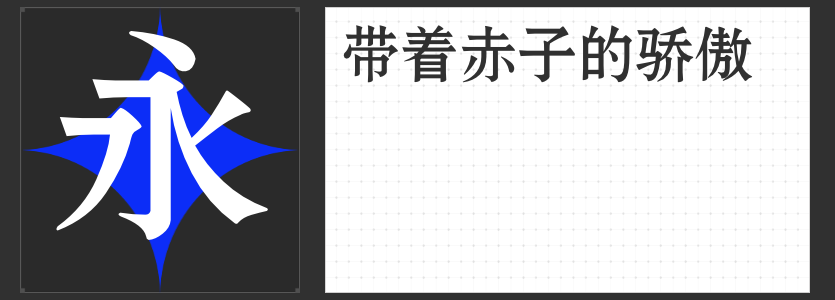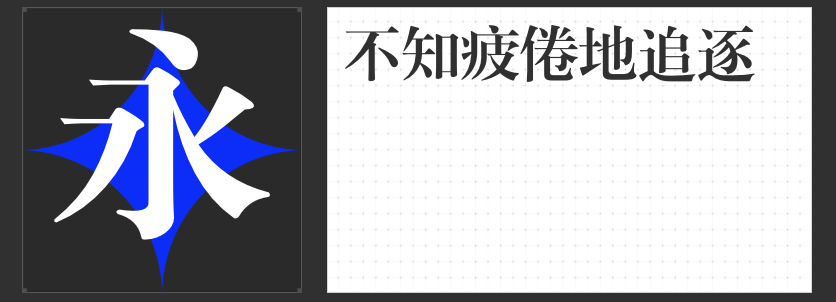
宋体之美:四款精选字库字体推荐
在字体的海洋中,宋体以其独特的韵味和端庄的风格,赢得了众多设计师的青睐。今天,我们为大家推荐四款精心挑选的宋体字体,让我们一同领略宋体的独特魅力。
1.励字大标宋简繁
以其横轻竖重、末端装饰精美的特点,展现了老宋体与黑体的完美结合。笔画间粗细变化自然,点、撇、捺、钩等笔画尖端犀利,字形端正清秀,刚劲有力。这款字体不仅保留了宋体的传统韵味,还融入了黑体的挺拔与稳重,适用于需要展现端庄与力量的设计场合。
2.高手兵克高雅宋
则以其优雅的风格和细长的字形,赢得了无数设计爱好者的喜爱。重心高、笔画细长的设计,使得这款字体在视觉上更加轻盈与灵动。无论是用于标题还是正文,都能展现出一种独特的优雅气质,适用于需要展现品味与格调的设计作品。
3.励字宋黑简
以黑体为原型,结合宋体的特点,打造出一款典雅、工整、严肃的字体。横竖笔画挺拔有力,结构均匀,笔法严谨,美观实用。这款字体不仅保留了黑体的清晰与易读性,还融入了宋体的端庄与稳重,适用于需要展现正式与专业的设计场合。
4.励字小标宋简
以其典型的宋体特征,展现了横细竖粗、笔画粗细变化自然的魅力。字形端正清秀,结构均匀,笔法严谨,美观实用。这款字体不仅适用于正文标题的设计,还能在各类需要展现端庄与正式感的场合中发挥出其独特的优势。
四款字体,各具特色,共同展现了宋体的独特韵味和广泛应用场景。无论是追求传统韵味还是现代简约,都能在这些字体中找到合适的表达。让我们一同感受宋体字体带来的视觉盛宴,让设计作品因它们而更加精彩。